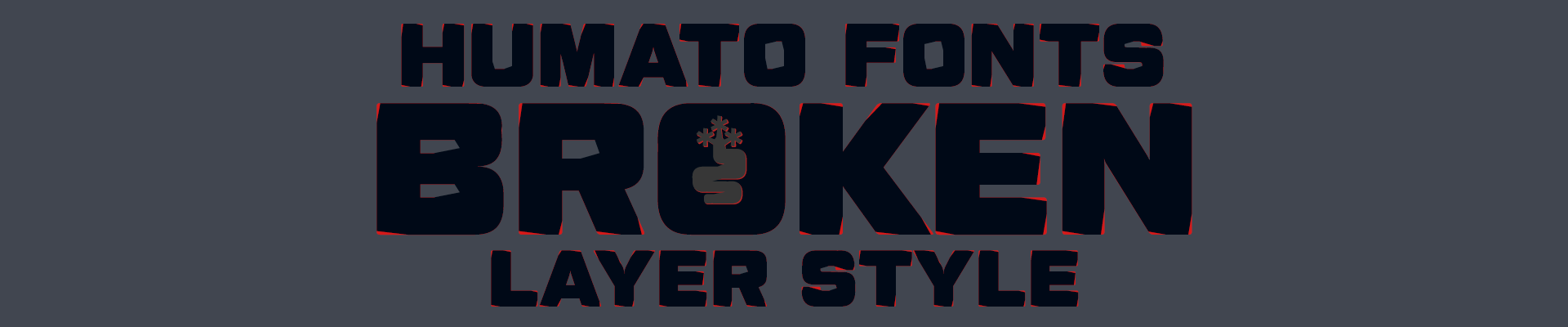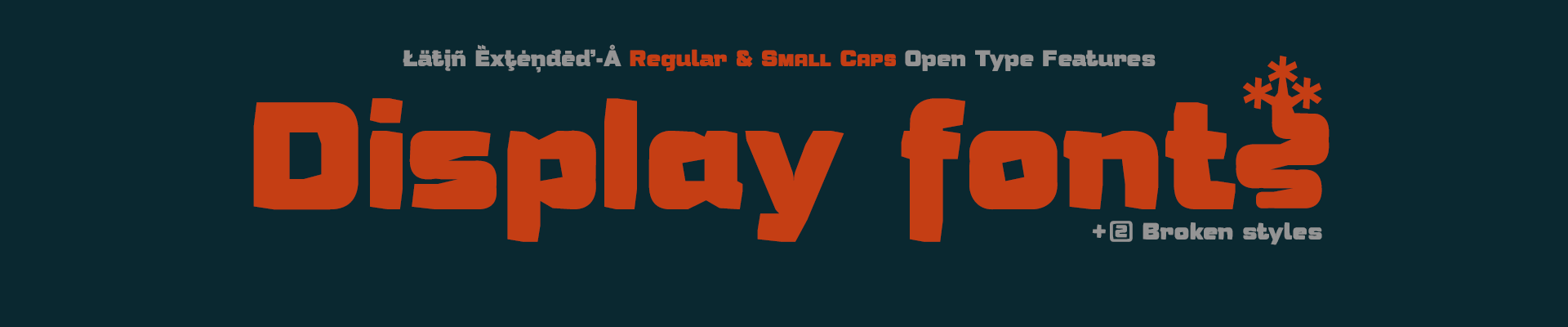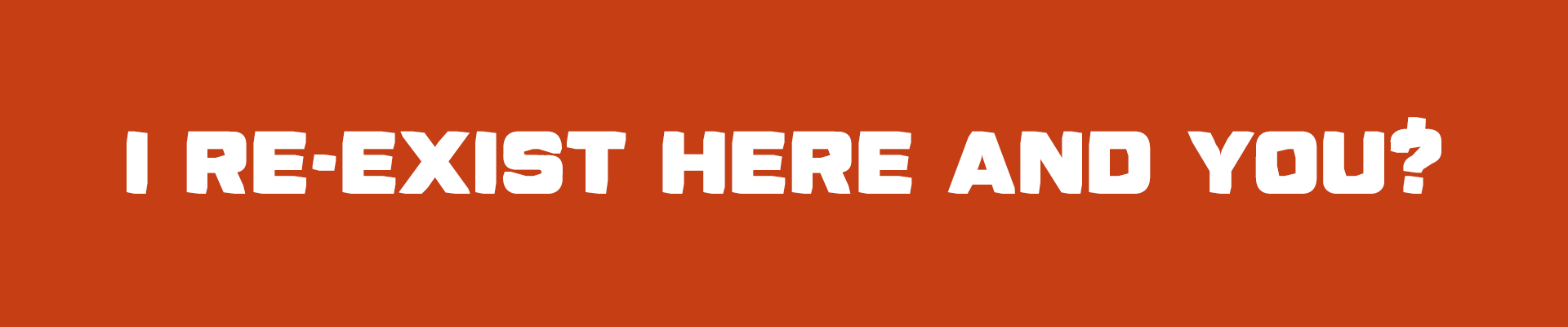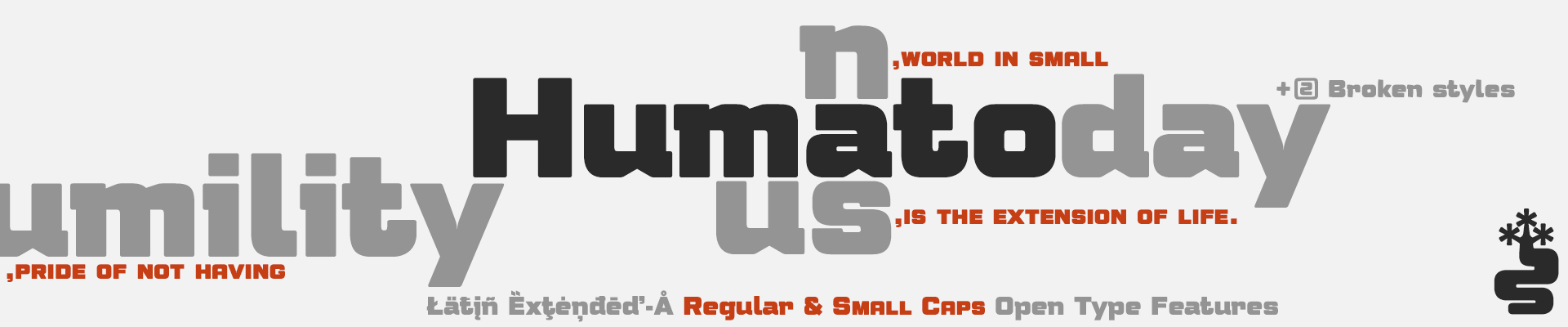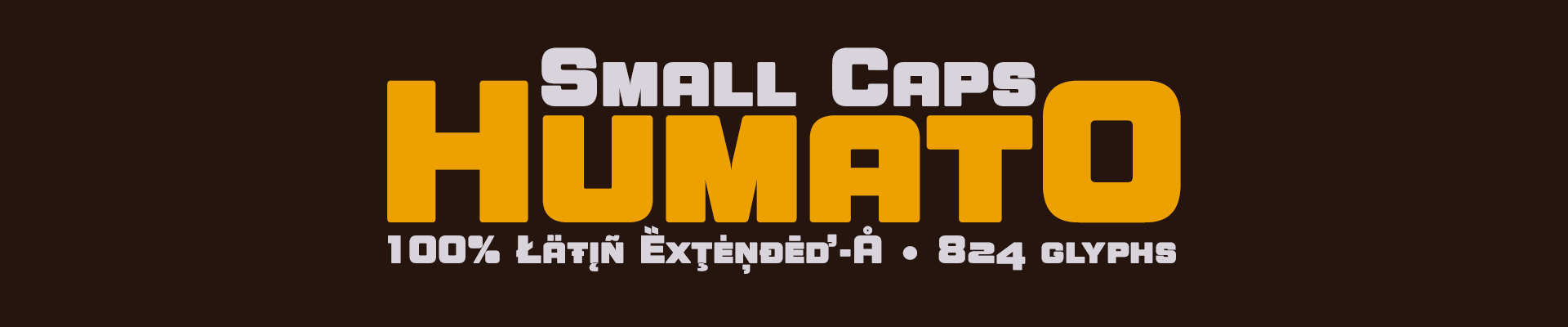
Dos estilos principales: Heavy y Small Caps (versalita).
Las fonts disponen de una minuciosa configuración de las Métricas y Kerning. Encontrarás 3 juegos de Mayúsculas, 5 juegos de minúsculas y 10 de números, además, incluyen caracteres alternativos y funciones Open Type avanzadas, además, dos versiones extra completas, de estilo roto, que también, se pueden usar como layer font.
Estilo: Sans Serif, Broken, Small Caps, Outline, Shadow
Proporción: Square, Heavy, Display
Humato es una familia de fonts display, muy gruesas, de proporción cuadrada y de esquinas redondeadas.
Dos estilos principales: Heavy y Small Caps (Versalita).
Las fonts disponen de una minuciosa configuración de las Métricas y Kerning. Encontrarás 3 juegos de Mayúsculas, 5 juegos de minúsculas y 10 de números, además, incluyen caracteres alternativos y funciones Open Type avanzadas, además, dos versiones extra completas, de estilo roto, que también se pueden usar como layer font.
Esta tipografía sans serif, proporciona gran impacto a los textos escritos con ella, su uso en diseño gráfico, editorial y publicidad garantiza originalidad, diferencia y máxima legibilidad.
Unas fuentes muy versátiles para carteles publicitarios, vídeo juegos, títulos de cine, logotipos, publicaciones, etc. Incluyen el símbolo del Bitcoin y otras Cripto Monedas.
La fuente «Humato Heavy dispone en su versión comercial de un juego de 841 glifos (Latin Extended-A), la versión Small Caps (versalita) 824 glifos, ambas con soporte para cualquier idioma europeo o centro europeo.